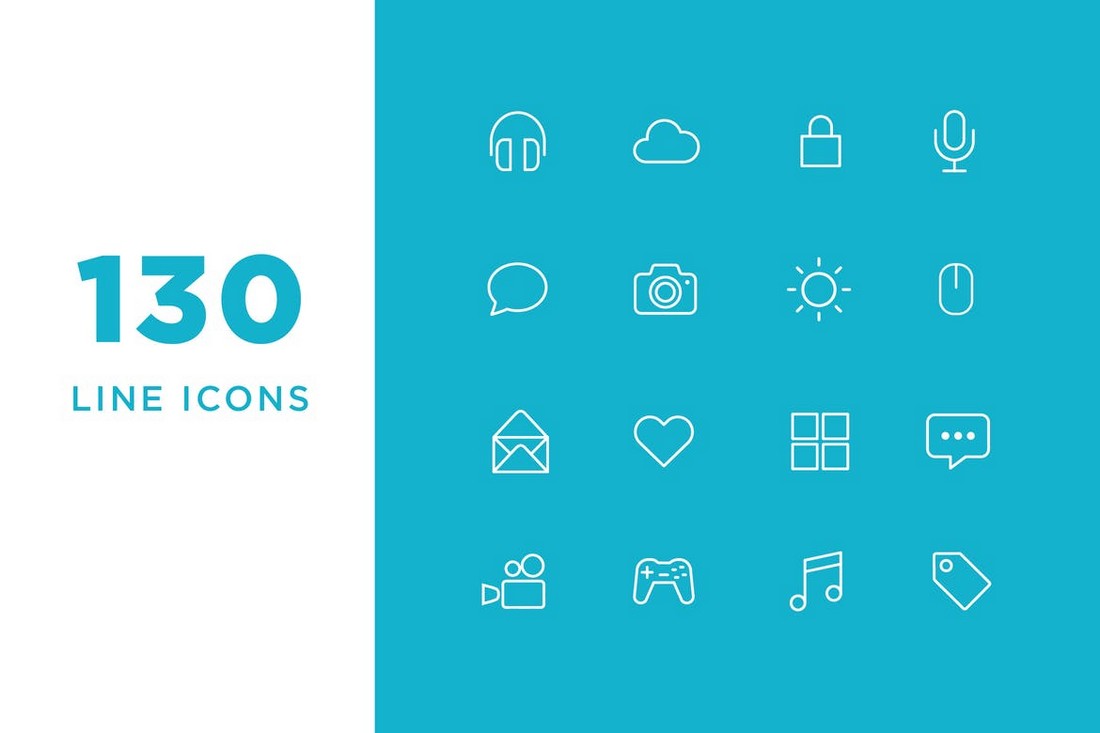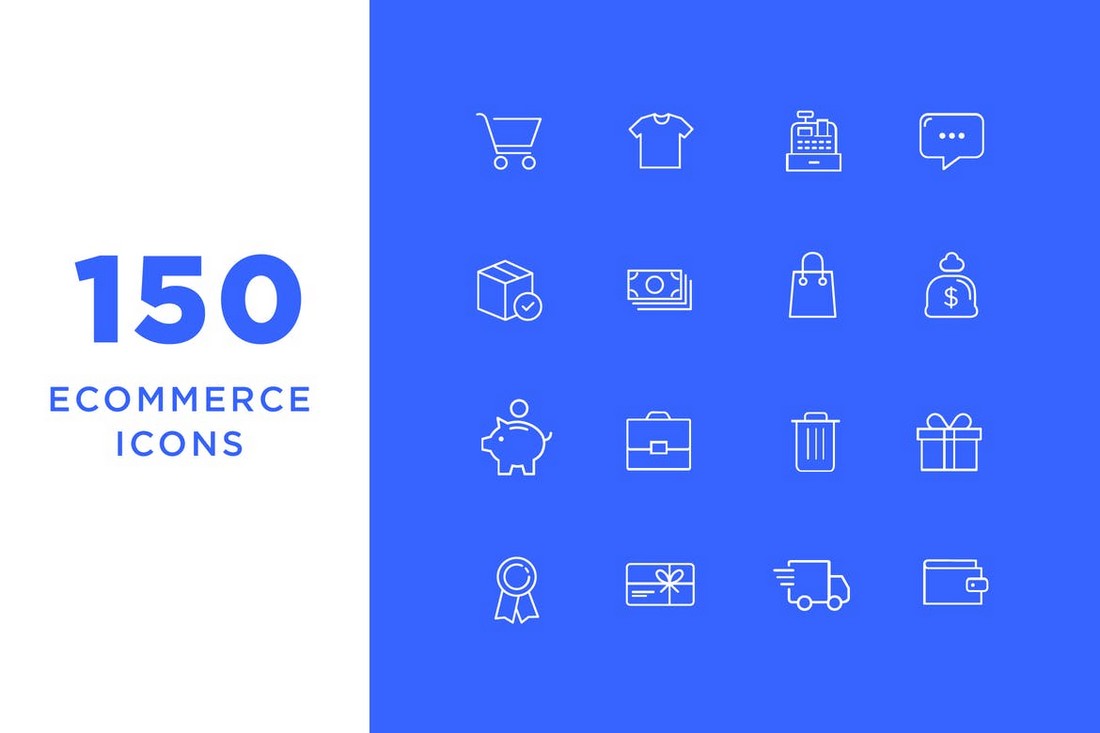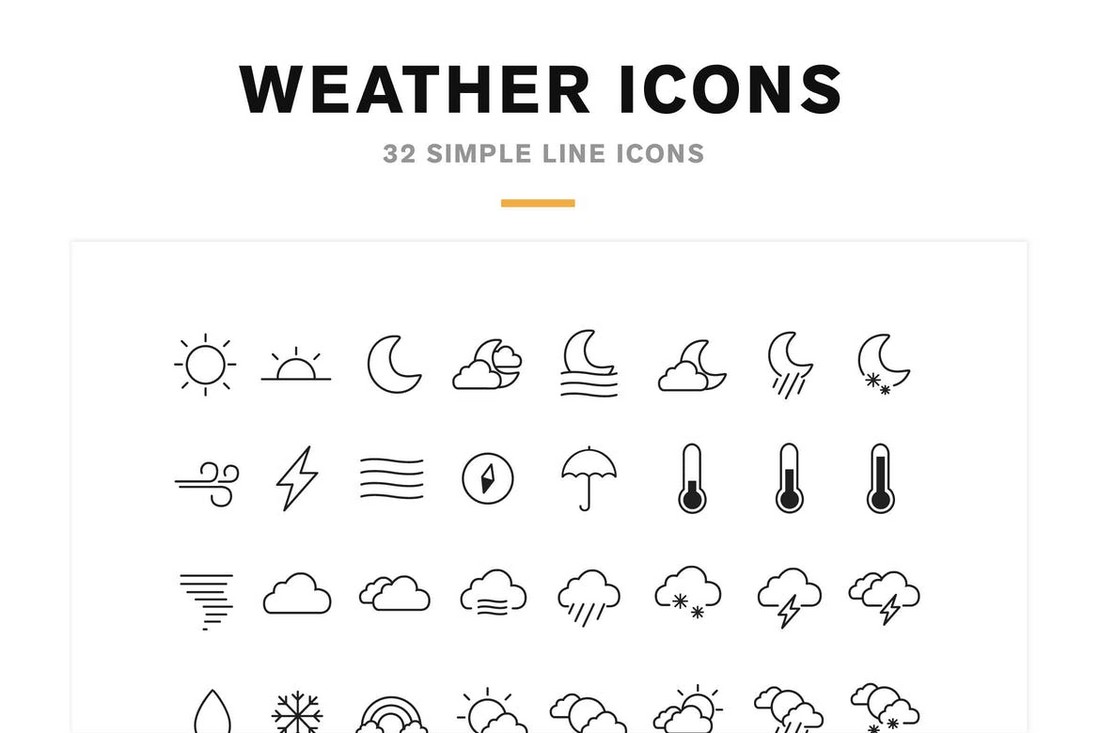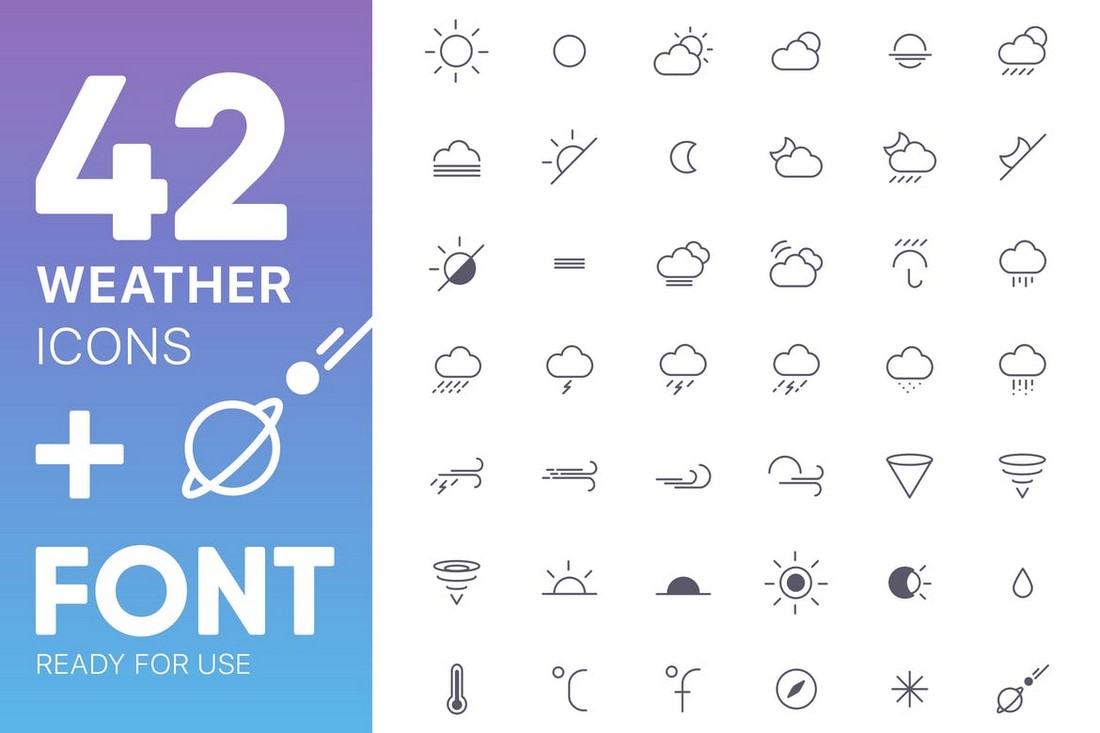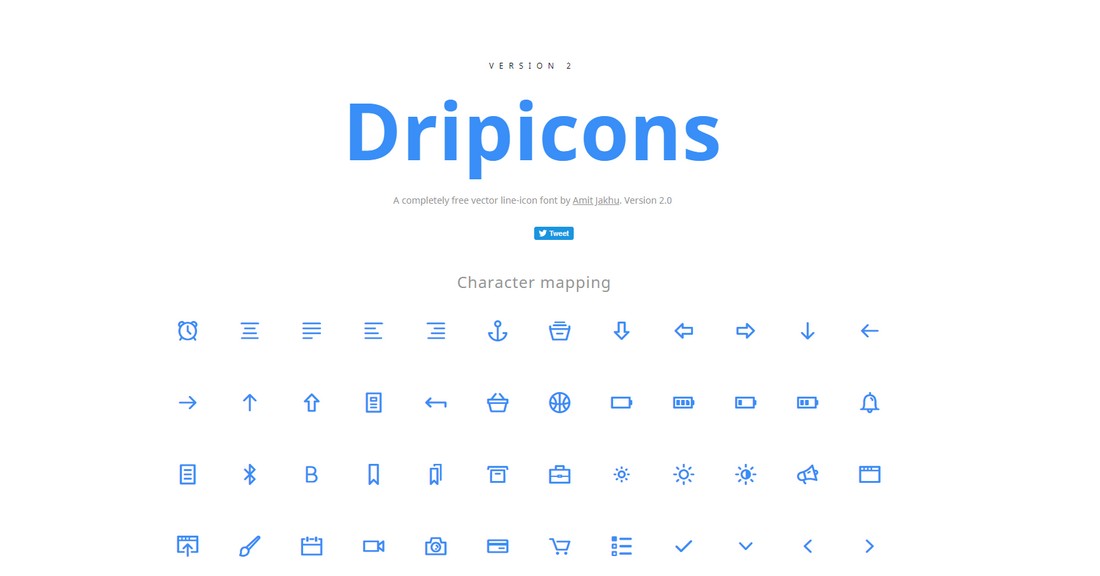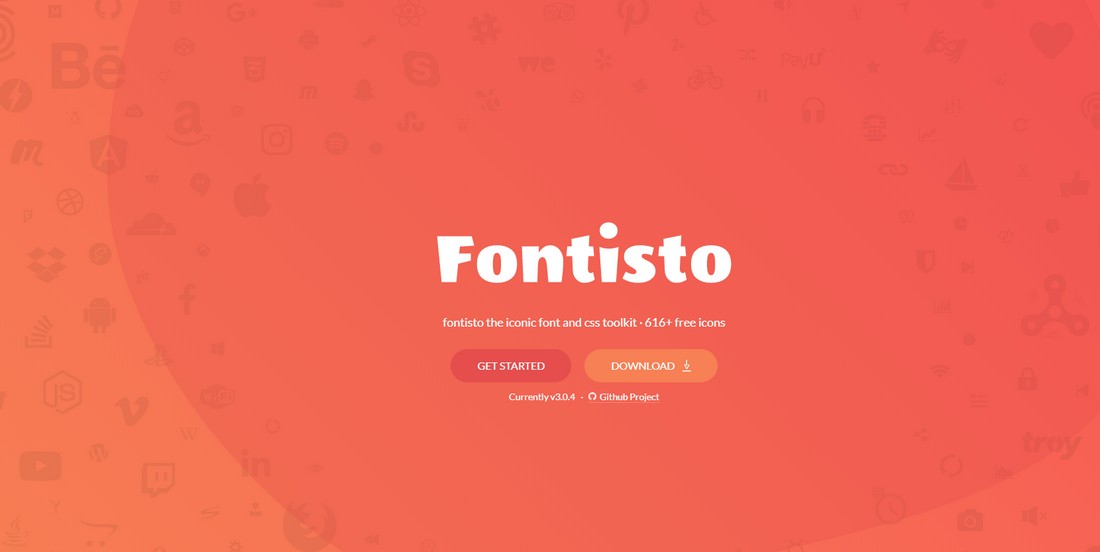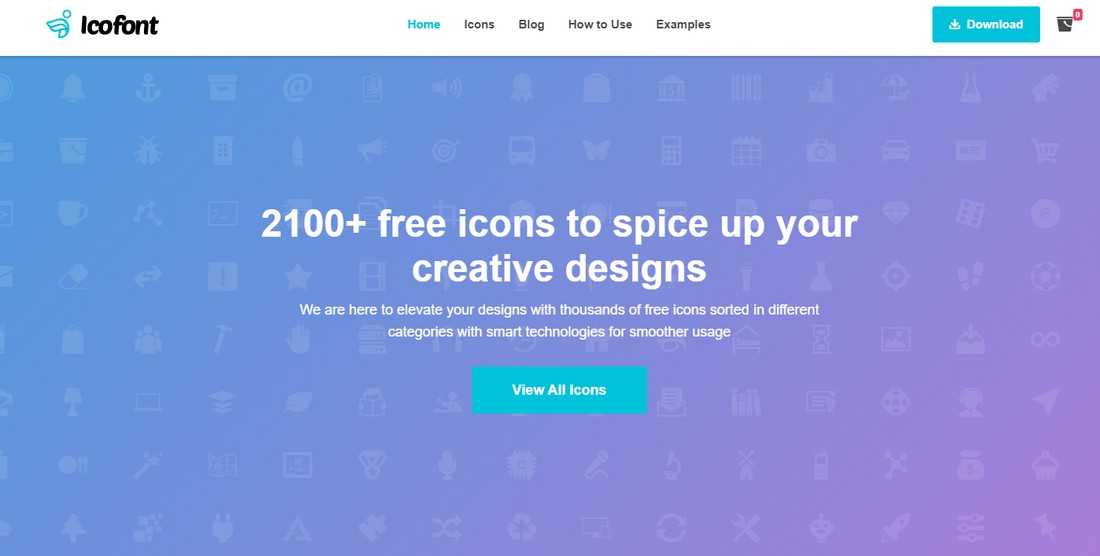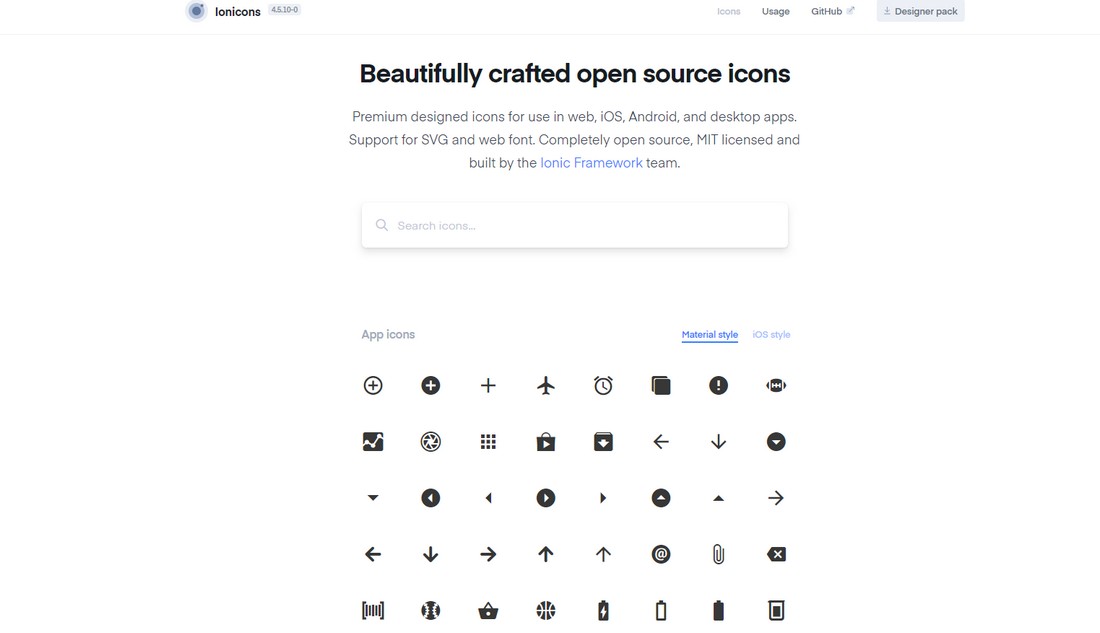
圖標(biāo)(Icon)字體是網(wǎng)站設(shè)計(jì)和UI設(shè)計(jì)中都無(wú)法缺少的最有用的元素之一。 今天,我們?yōu)槟銕?lái)了一些現(xiàn)代和創(chuàng)意的圖標(biāo)集合,你可以在你的網(wǎng)站設(shè)計(jì)或用戶界面設(shè)計(jì)中使用它們,以幫助你的設(shè)計(jì)增加一些獨(dú)特的視覺特點(diǎn)和吸引力。
使用圖標(biāo)字體,你不必再依賴PNG文件庫(kù),無(wú)需使用矢量文件來(lái)調(diào)整圖標(biāo)的大小和進(jìn)行編輯即可使其適合你的網(wǎng)站設(shè)計(jì)。 而且,更重要的是,你不必再針對(duì)各種屏幕尺寸來(lái)單獨(dú)去優(yōu)化圖標(biāo)。
但是,找到適合你的設(shè)計(jì)項(xiàng)目的正確圖標(biāo)字體可能是一項(xiàng)挑戰(zhàn)。 我們希望使這一過(guò)程更加容易。 通過(guò)瀏覽我們精選的圖標(biāo)字體,希望可以幫助你更快更好的完成你的項(xiàng)目(一定要看看我們的選擇圖標(biāo)字體的技巧,以幫助你入門)。
1.Icofont – Free Creative Icon Font
Icofont提供了具創(chuàng)意的圖標(biāo)字體,你可以免費(fèi)下載和使用。 該字體包括30個(gè)不同類別的2100多個(gè)圖標(biāo),例如貨幣,社交,品牌徽標(biāo)等。 使用此工具的好處之一是,它既可以SVG格式提供,也可以字體的形式提供。
2.Font Awesome – Free Icon Font
Font Awesome可能是Internet上最受歡迎的圖標(biāo)字體,具有7000多個(gè)圖標(biāo)。 超過(guò)1億個(gè)網(wǎng)站都在使用它,其中包括麥當(dāng)勞和耶魯大學(xué)等品牌。 它包含許多有用的功能。
3.Ionicons – Free Minimal Icon Font
Ionicons是另一組具有極簡(jiǎn)風(fēng)格和簡(jiǎn)單設(shè)計(jì)特征的創(chuàng)意圖標(biāo)。 該圖標(biāo)字體專為網(wǎng)站設(shè)計(jì)和移動(dòng)用戶界面設(shè)計(jì)而準(zhǔn)備,并且與iOS和Android平臺(tái)兼容。 它總共具有1100多個(gè)圖標(biāo),根據(jù)MIT開源許可證獲得許可。
4.150 eCommerce Icons with Icon Font
這是具有現(xiàn)代簡(jiǎn)約圖標(biāo)設(shè)計(jì)的獨(dú)特圖標(biāo)的集合,包括150個(gè)不同的圖標(biāo),你可以在各種電子商務(wù)設(shè)計(jì)中使用它們。 這些圖標(biāo)有EPS,AI,SVG和字體版本。
5.130 Vector Line Icons & Icon Font
該資源文件匯總包括與娛樂,多媒體,在線活動(dòng),生活方式等相關(guān)圖標(biāo)的混合集合。 該程序包總共包含130個(gè)圖標(biāo),你可以將其用作圖標(biāo)字體,也可以使用其矢量EPS和AI文件根據(jù)自己的喜好進(jìn)行編輯和自定義。
6.Weather Icons and Icon Font
Weather通常用于許多不同類型的Web和UI設(shè)計(jì)中,尤其是在移動(dòng)用戶界面中。 使用此工具包,你可以從42個(gè)與天氣相關(guān)的獨(dú)特圖標(biāo)中進(jìn)行選擇。 這些圖標(biāo)還可以使用AI,PSD,SVG和字體格式。
7.32 Weather Icons and Font
與上面的圖標(biāo)字體包很相似,此包具有一組極簡(jiǎn)線條風(fēng)格的圖標(biāo)。 它還包括32種時(shí)尚的天氣圖標(biāo),格式多樣,包括AI,SVG,EPS和字體。 干凈簡(jiǎn)潔的設(shè)計(jì)使這些圖標(biāo)適用于所有類型的業(yè)務(wù)和專業(yè)設(shè)計(jì)。
8.Fontisto – Free Modern Icon Font
Fontisto是另一個(gè)很棒的免費(fèi)圖標(biāo)字體,具有多種類別現(xiàn)代時(shí)尚圖標(biāo)。 這些圖標(biāo)可完全縮放,并且在Retina顯示屏上看起來(lái)很棒。 它也可以完全免費(fèi)用于商業(yè)項(xiàng)目。
9.Dripicons – Free Vector Line-Icon Font
Dripicons是一個(gè)線條圖標(biāo)的集合,具有平滑和極簡(jiǎn)的設(shè)計(jì)。 這些圖標(biāo)具有適合于網(wǎng)站設(shè)計(jì)和移動(dòng)用戶界面設(shè)計(jì)的現(xiàn)代布局。 它也可以免費(fèi)用于商業(yè)項(xiàng)目。
10.Typicons – Free Simple Icon Font
Typicons帶有一組輕巧和簡(jiǎn)單的圖標(biāo),可在Web和本機(jī)應(yīng)用程序用戶界面上使用。 字體包括超過(guò)330個(gè)獨(dú)特的圖標(biāo)設(shè)計(jì),這些設(shè)計(jì)在多個(gè)類別中具有可伸縮的設(shè)計(jì)。
選擇圖標(biāo)字體的5個(gè)技巧
以下是一些技巧,可幫助你為各種類型的Web和UI設(shè)計(jì)選擇最佳的圖標(biāo)字體。
2.響應(yīng)性(Make Sure it’s Responsive)
選擇任何類型的圖標(biāo)時(shí),圖標(biāo)的響應(yīng)能力可能是最重要的功能。 這也是圖標(biāo)字體吸引人的地方,因?yàn)樗鼈兺ǔW銐蜢`敏,在所有類型的屏幕尺寸和設(shè)備上看起來(lái)都一樣。
仔細(xì)檢查以確保圖標(biāo)具有響應(yīng)性,特別是如果你使用的是SVG版本的圖標(biāo)。
3.選擇合適的主題(Pick Appropriate Themes)
圖標(biāo)字體有各種樣式和主題。 例如大綱圖標(biāo),平面設(shè)計(jì)圖標(biāo),簡(jiǎn)約圖標(biāo)以及不同主題的網(wǎng)站設(shè)計(jì)圖標(biāo)等等。 根據(jù)你正在處理的項(xiàng)目的類型,你可以自行選擇符合主題的正確圖標(biāo)字體。
4.顏色以及可定制性(Colors and Customization)
圖標(biāo)字體的許多好處之一是,它允許你根據(jù)自己的喜好自定義圖標(biāo)。 大多數(shù)現(xiàn)代圖標(biāo)字體甚至都允許你從多個(gè)圖標(biāo)版本中進(jìn)行選擇,包括填充和輪廓版本。
圖標(biāo)對(duì)于設(shè)計(jì)項(xiàng)目來(lái)說(shuō)是一個(gè)可以增加亮點(diǎn)的元素,使用合適的圖標(biāo)可以幫助你獲得更多的關(guān)注度并增加設(shè)計(jì)的風(fēng)格。